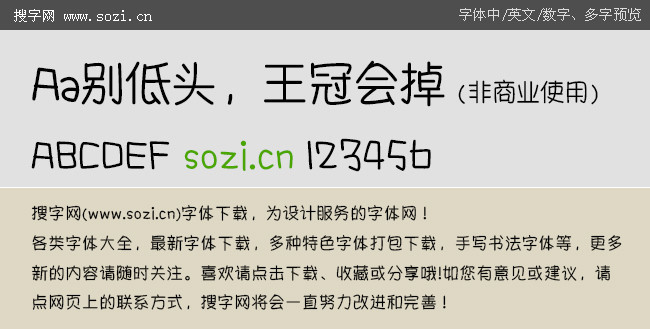
Aa別低頭,王冠會掉(非商業(yè)使用)
搜字網(wǎng)給大家提供一款A(yù)a別低頭,王冠會掉(非商業(yè)使用)中文字體下載,該字體線條粗細適中,筆畫處理上簡單,整體效果出色,適合海報設(shè)計、包裝畫冊等宣傳廣告等應(yīng)用(此字體為個人非商用版,商用可以聯(lián)系QQ:1006760504)。